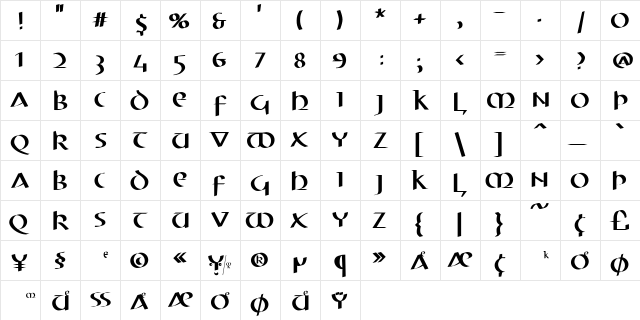
Copyright: DIESE UNZIALE WURDE DIREKT AM BILDSCHIRM KONSTRUIERT am 21.6.92 von Manfred Klein fuer Klaus Burkhardt. Neue Version (ElectrUnciale\) am 8. Juli 2005. Hello, Klaus, is it OK on your cloud no. 9? Please wait!